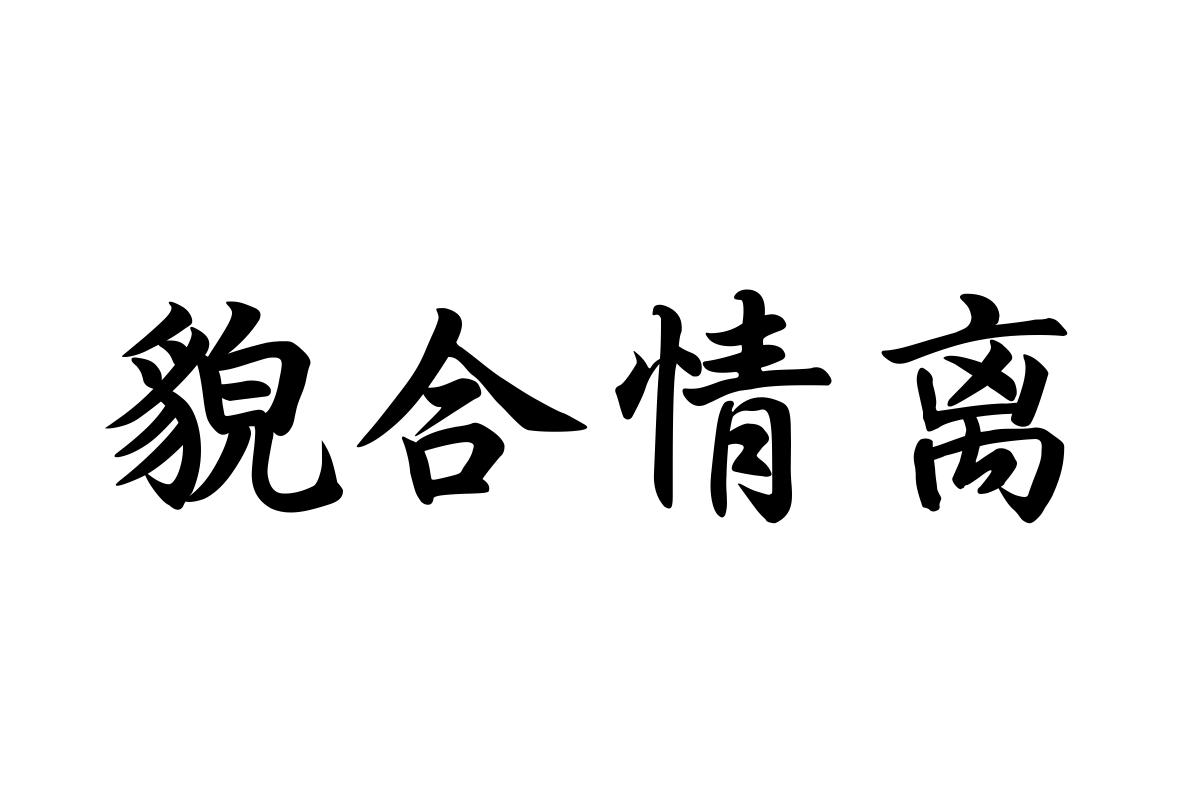
三极湘乡体是湖南长沙的著名书法家王羲之(303年—361年)所创行书字体之一。这种字体以其独特的风格和结构,在中国书法史上占有重要地位。
三极湘乡体的特点是:笔画流畅、结构严谨、笔势雄健。它既有隶书的规整,又有楷书的端庄,同时又有草书的灵动。这种字体既有古典美,又不失时代感,因此深受人们喜爱。
三极湘乡体的书写技巧主要有以下几点:
1. 笔锋要有力,既要有力度又要有弹性,这样才能写出流畅的笔画。
2. 笔法要灵活,要根据字的结构和个人的风格来调整笔画的粗细、长短、弯曲等。
3. 运笔要平稳,要保持一定的速度和节奏,这样才能写出稳定而有力的笔画。
4. 要注意字的整体结构,要把握好每个字的平衡和协调。
5. 要多练习,多体会,多观察,才能更好地掌握三极湘乡体的书写技巧。